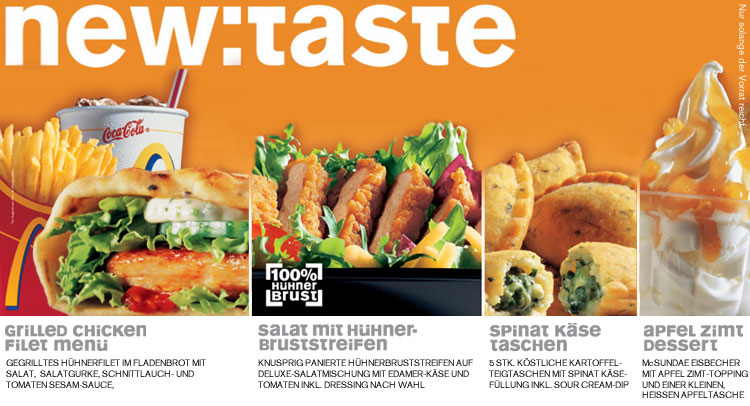
"relativ neu" und keine Ahnung welche: kino.de
Kennt Ihr die Schrift von kino.de? Ich meine die Schrift, wo die Versalien und Gemeinen gleiche Höhe haben und die Schrift daraus gemixt ist?
Die Schrift kommt wie bei McDonald's aus der Ecke von
Hab den Font beim Vorspann zu "Transporter - the mission" gesehen. Kann mich aber auch irren :oops:
Würd mich einfach tierisch interessieren, ob und welche "ähnlichen" fonts es zu uniF gibt.
Könnte mir sogar vorstellen die uniF zu bestellen, hätt aber gern Vergleichsmaterial :?:
Aber unicase war schon mal ein super Stichwort zum Suchen.